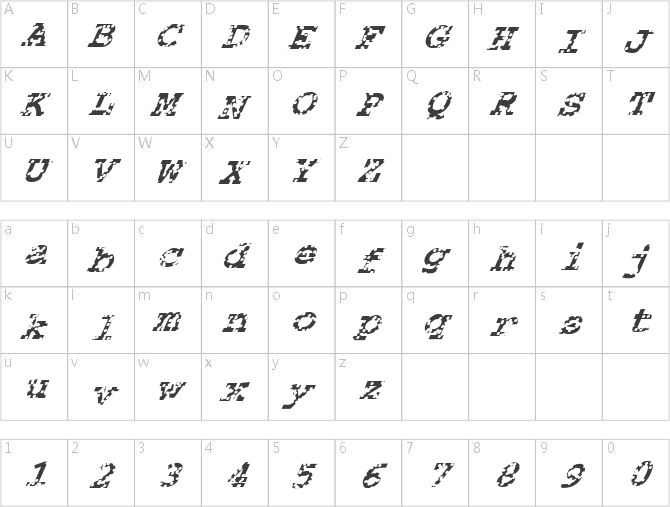
FZ BASIC 54 HOLEY ITALIC 詳情頁
FZ BASIC 54 HOLEY ITALIC字體字庫是一款讓人賞心悅目、百看不厭的英文字體,適合各類廣告和產(chǎn)品包裝設(shè)計應(yīng)用,字體大小0.12MB,格式為ttf字體,上傳用戶是后天的昨天,作者/版權(quán)方為未知